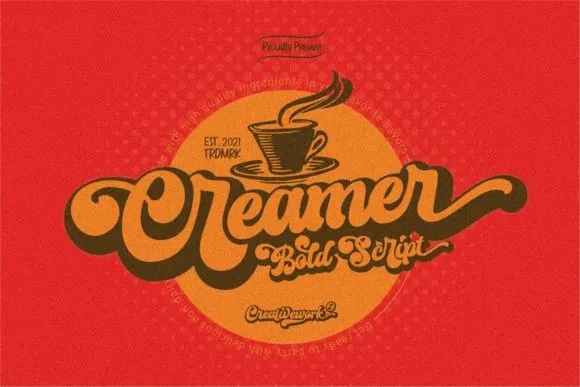
Creamer Font – Download Grátis
Aqui está uma versão do texto conforme as regras solicitadas: Inspirada nos logotipos das marcas TV dos anos 70 e 80, a nova fonte “Creamer Font” leva você para um mundo colorido e vibrante. Inspirado no bom gosto e na cor vibrante da cultura pop do período, essa tipografia fornece uma dose de nostalgia com o seu equilíbrio entre bold e confiante. Perfeita tanto para revistas vintage quanto para gráficos modernos, a “Creamer Font” é perfeita para aqueles que desejam dar um toque nostálgico e vibrante em suas criações digitais, seja em projetos de design editorial ou gráficos web. Inspirada na cultura pop dos anos 70 e 80, essa fonte retrata com destreza o bom gosto colorido que marcava esse período, permitindo aos criativos expressar a nostalgia de forma elegante e vibrante no seu próximo projeto.